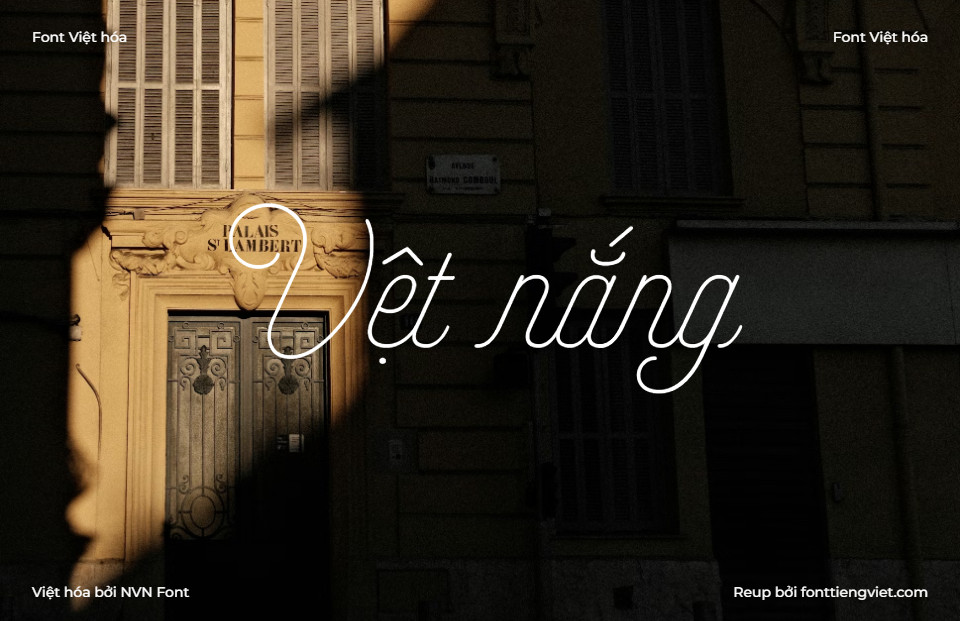
Font Việt hoá NVN Selfie Light
Giới thiệu về Font Việt hoá NVN Selfie Light
Trong thế giới thiết kế đồ họa hiện đại, việc lựa chọn một bộ Font Miễn Phí chất lượng luôn là ưu tiên hàng đầu của các bạn học sinh và sinh viên. Font Việt hoá NVN Selfie Light nổi lên như một hiện tượng nhờ vẻ đẹp thanh mảnh, tinh tế và vô cùng hiện đại. Đây là phiên bản được tối ưu hóa hoàn toàn cho bảng mã Telex và VNI, giúp người dùng dễ dàng gõ tiếng Việt mà không lo gặp lỗi hiển thị hay mất nét. Với đường nét thanh thoát, bộ phông chữ này mang đến cảm giác nhẹ nhàng, bay bổng, rất phù hợp cho những dự án mang tính thẩm mỹ cao và đòi hỏi sự tỉ mỉ trong từng chi tiết nhỏ nhất.
Đặc điểm nổi bật của Font Việt hoá NVN Selfie Light
Đúng như tên gọi của mình, Font Việt hoá NVN Selfie Light sở hữu độ dày nét chữ cực kỳ mảnh mai (lightweight), tạo nên một không gian thiết kế thoáng đãng và sang trọng. Các ký tự được uốn lượn mềm mại, lấy cảm hứng từ những nét vẽ tay thủ công nhưng vẫn giữ được sự chỉn chu của kỹ thuật số. Điều này giúp bộ font trở nên đa năng, từ việc trang trí bìa sách, làm slide thuyết trình học tập cho đến thiết kế các tấm thiệp chúc mừng ý nghĩa. Sự đồng nhất trong khoảng cách giữa các chữ cái cũng giúp văn bản trở nên dễ đọc và bắt mắt hơn trên mọi thiết bị hiển thị.
Ứng dụng thực tiễn của Font Việt hoá NVN Selfie Light
Đối với các bạn học sinh, Font Việt hoá NVN Selfie Light là công cụ đắc lực để làm mới các bài báo cáo hay dự án học tập. Thay vì sử dụng những phông chữ hệ thống khô khan, việc thay thế bằng Selfie Light sẽ giúp nội dung trở nên sinh động và có dấu ấn cá nhân hơn. Trong môi trường nhà trường, thầy cô cũng có thể sử dụng bộ chữ này để thiết kế các poster thông báo hoặc vinh danh học sinh, tạo ra một không gian sư phạm chuyên nghiệp nhưng không kém phần gần gũi và hiện đại.
Lưu ý khi sử dụng Font Việt hoá NVN Selfie Light trong thiết kế
Dù mang vẻ đẹp cuốn hút, người dùng cần lưu ý phối hợp Font Việt hoá NVN Selfie Light với các phông chữ không chân (Sans-serif) khác để tạo sự cân bằng cho bố cục. Vì nét chữ khá mảnh, bạn nên sử dụng kích thước từ trung bình đến lớn để đảm bảo độ tương phản tốt nhất trên các nền màu đậm hoặc ảnh chụp. Ngoài ra, việc áp dụng các hiệu ứng đổ bóng nhẹ hoặc tăng khoảng cách dòng sẽ giúp đoạn văn bản trở nên thanh lịch và tinh tế hơn rất nhiều, tránh gây rối mắt cho người xem khi theo dõi nội dung dài.
Tổng kết lại, đây là một lựa chọn không thể bỏ qua cho những ai đang tìm kiếm sự mới mẻ và tinh tế trong nghệ thuật chữ viết. Sự kết hợp hoàn hảo giữa tính thẩm mỹ và khả năng hiển thị tiếng Việt mượt mà đã giúp bộ font này chiếm trọn tình cảm của cộng đồng sáng tạo tại Việt Nam. Nếu bạn đang muốn nâng cấp các sản phẩm thiết kế của mình lên một tầm cao mới, hãy truy cập ngay vào hệ thống Font Miễn Phí, Font Việt Hóa, Font Việt hoá NVN Selfie Light để tải về và trải nghiệm hoàn toàn miễn phí. Đừng quên chia sẻ bộ font tuyệt vời này với bạn bè để cùng nhau tạo nên những tác phẩm đồ họa xuất sắc nhất nhé.